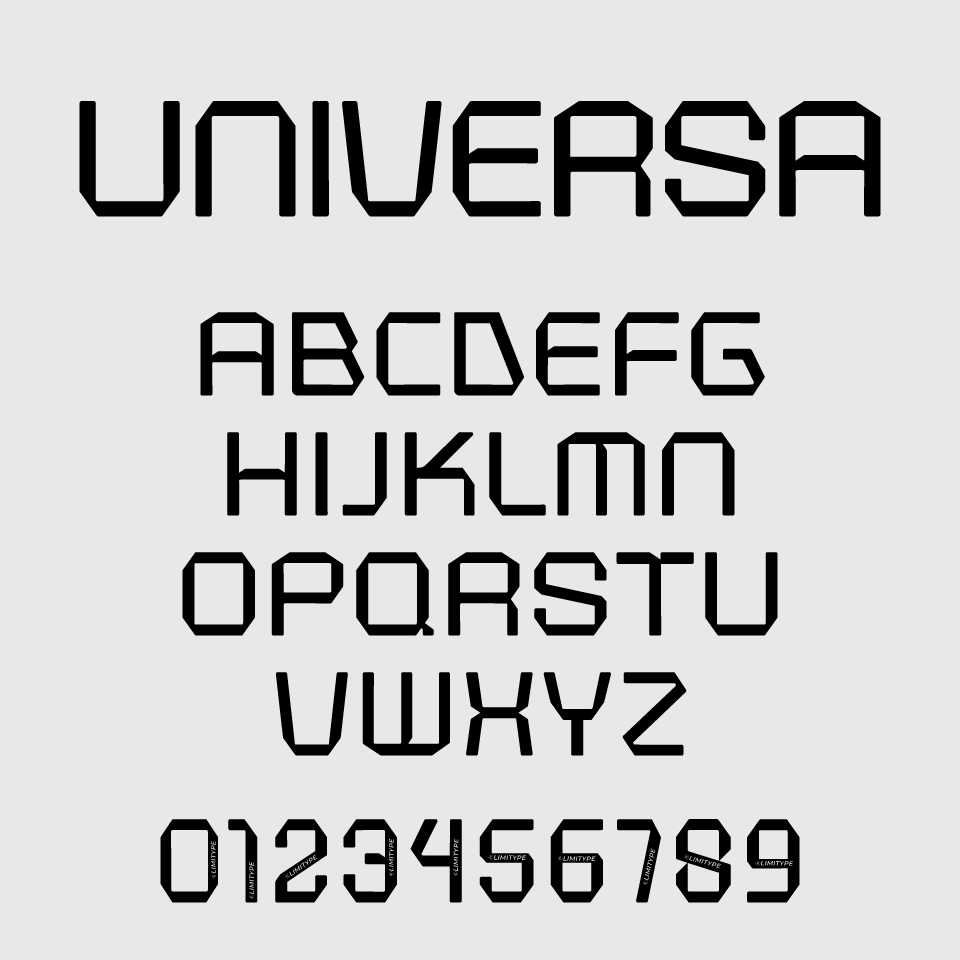
Universaフォントは、直線と角張ったラインで構成された、インダストリアル感のある幾何学フォントです。
角を落としたハニカム形状が特徴的で、デジタル感・近未来感な雰囲気をもつフォントです。
宇宙っぽさやテクノ系やSF作品の世界観にぴったりです。テキストとして読むというよりも、ロゴタイプとして「魅せる」「視る」などのタイポグラフィとして活躍するディスプレイフォントです。